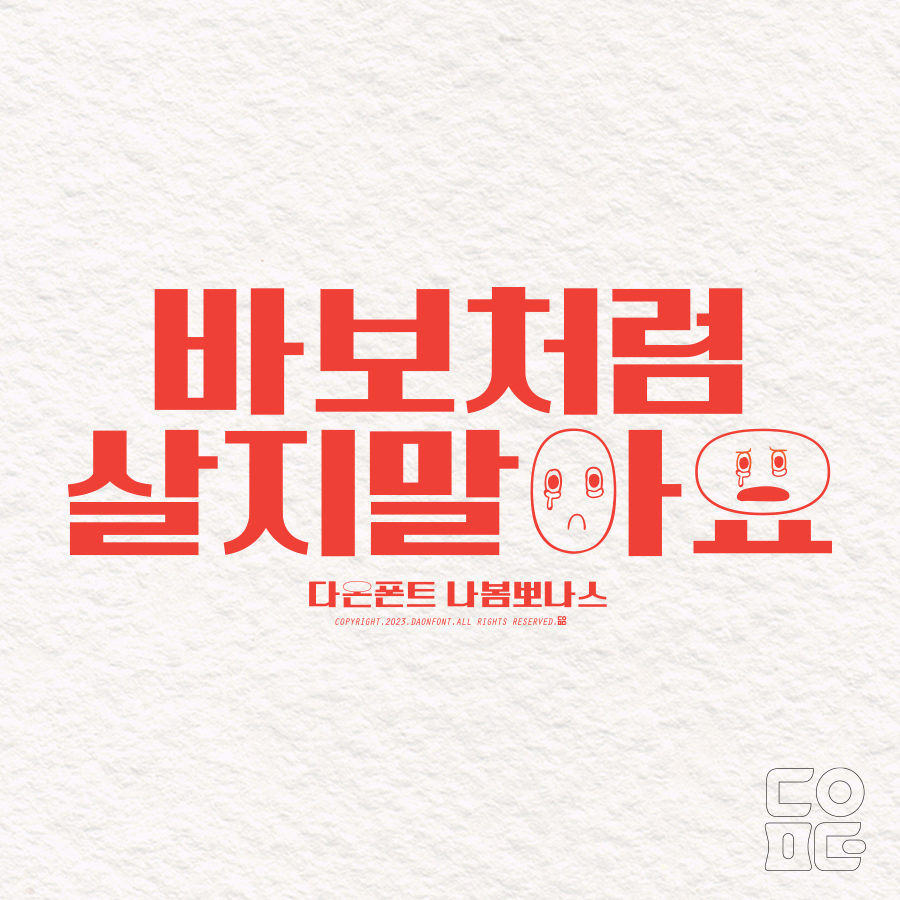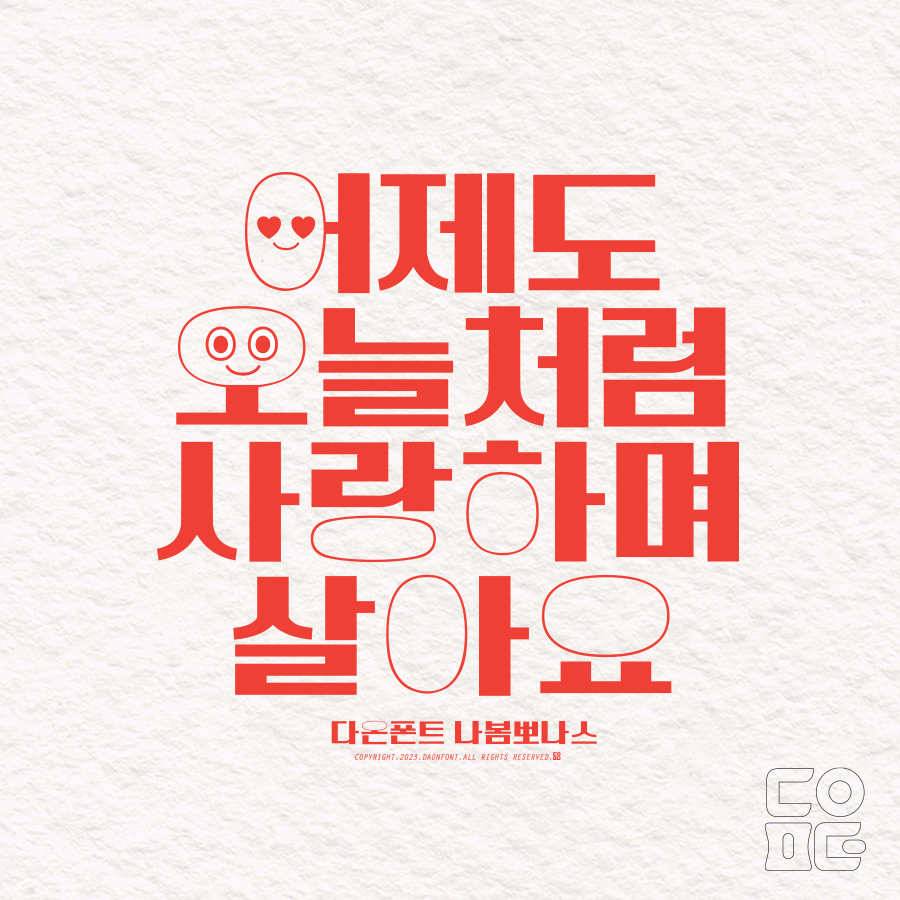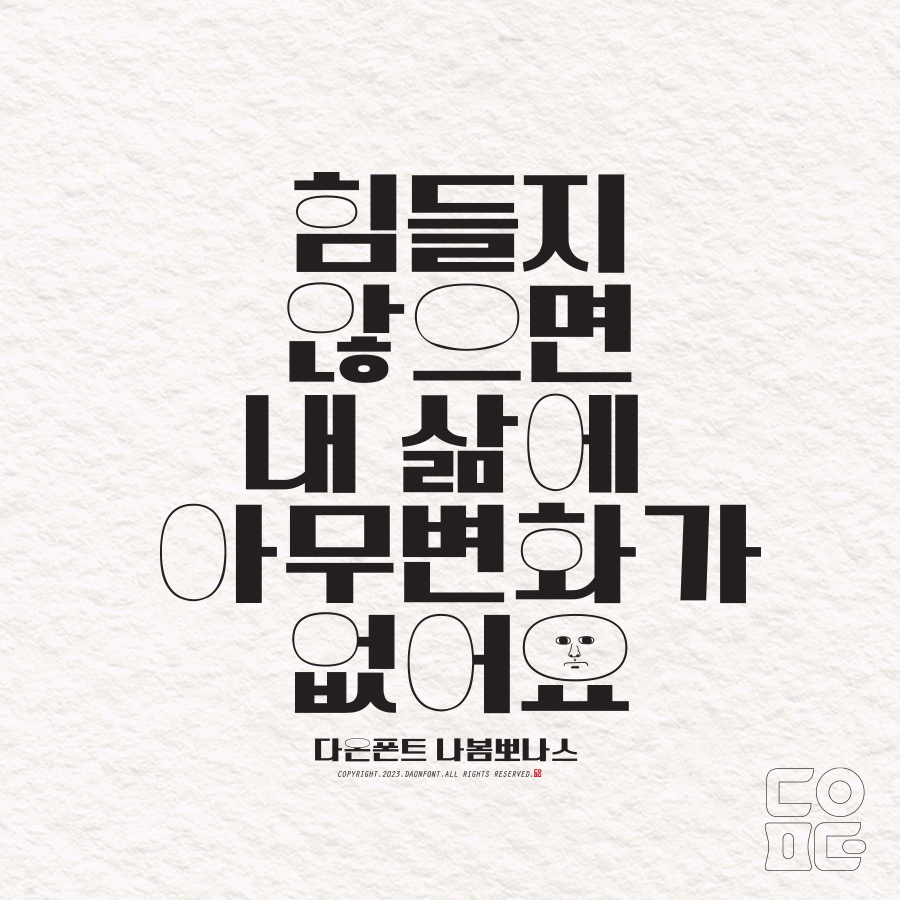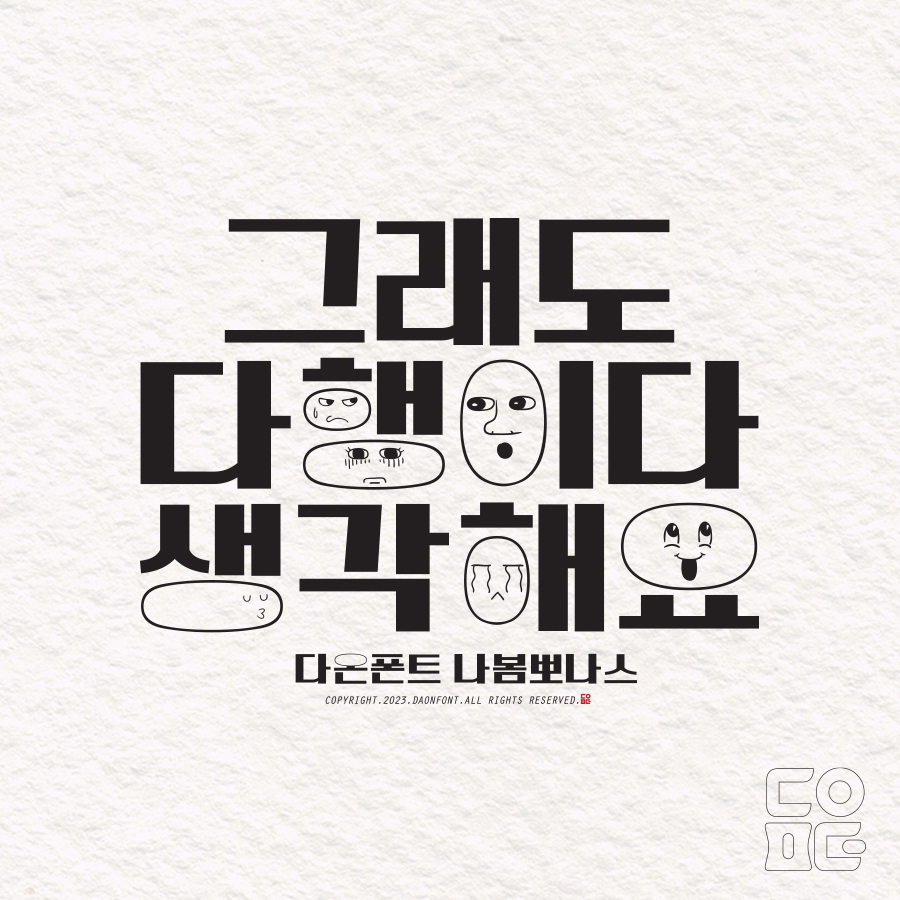
4월 신서체 다온폰트 "나봄뽀나스" 출시
4월 신서체인 다온폰트 "나봄뽀나스"가 업데이트 되었습니다.
다온폰트 "나봄뽀나스"는 제목용 서체로 제작된 서체로
2,780자, 딩벳세트 구성되어 있습니다.
다온폰트 "나봄뽀나스"는 글씨에 표정을 넣을 수 있도록 준비되었습니다.
나봄쪼꼬미 디자인소스를 사용하시면 타이틀디자인에서도 제법 유용하게 사용하실 수 있습니다.